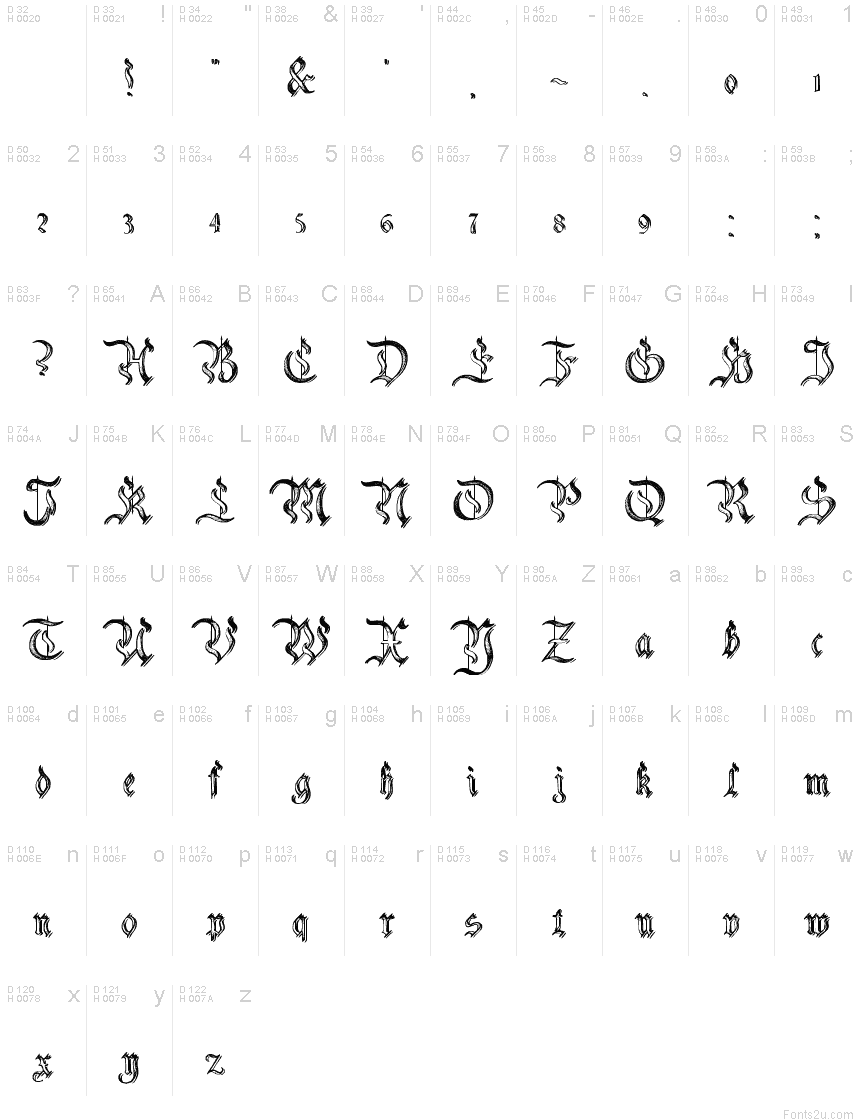
Charterwell No5 od PJL to darmowy gotycki krój pisma, który sprawia wrażenie wyjętego prosto ze starego, iluminowanego manuskryptu. Ciężkie czarne kreski, dłutowane kąty i zarysowane wewnętrzne cieniowanie nadają każdej literze teksturę ręcznie rzeźbionego drzeworytu, który aż skrzypi od starości. Rytm jest gęsty i dramatyczny, dzięki czemu nawet krótkie słowo zamienia się w wyrazisty, ozdobny baner.
Dzięki Charterwell No5 nagłówki natychmiast zyskują mroczny, historyczny klimat, idealny na okładki książek fantasy, podręczniki do gier RPG, logotypy zespołów metalowych, szyldy pubów lub tawern, plakaty tematyczne czy branding jarmarków średniowiecznych. Ten darmowy font najlepiej sprawdza się w większych rozmiarach, gdzie jego atramentowe cieniowanie i detale mogą w pełni wybrzmieć; połącz go z czystym krojem bezszeryfowym w tekście głównym, aby zachować czytelność i stabilność wizualną projektu.
Charterwell No5